Responsive Webdesign: Worauf es beim Einsatz reaktionsfähiger Typografie ankommt
Webdesign ist zu 95 Prozent Typografie, hat Oliver Reichenstein mal gesagt [1]. In der Tat kommt man als Webdesigner nicht umhin, sich auch im Kontext von Responsive Webdesign mit typografischen Fragestellungen auseinanderzusetzen. Welchen Einfluss eine veränderte Darstellungsfläche auf das typografische Erscheinungsbild hat und mit welchen gestalterischen und technischen Mitteln Webdesigner darauf reagieren können, steht im Mittelpunkt der folgenden Betrachtungen. Ebenso gilt es, weitere Einschränkungen in „mobilen Situationen“ wie lange Ladezeiten und ungünstige Lichtverhältnisse zu berücksichtigen.
Schriftgrößen anpassen
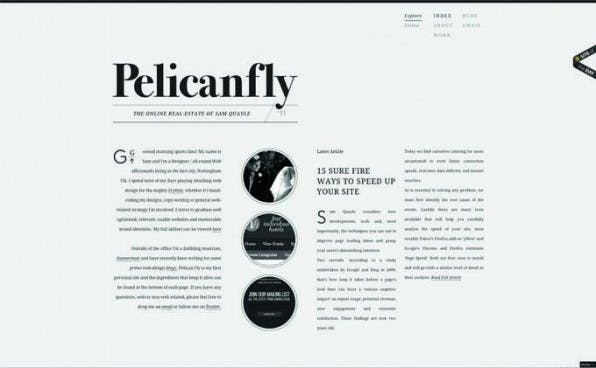
Wenn Websites auf verschiedene Bildschirmgrößen und Geräte reagieren sollen, brauchen sie dazu eine gewisse Flexibilität, die vor allem durch ein flexibles Raster in Kombination mit Media Queries erreicht wird. Wenn Spaltenbreiten, Bildgrößen und andere Dimensionen sich ändern, liegt es nahe, auch die typografische Erscheinung anzupassen. Bei veränderter Bildschirmgröße müssen dabei zwei Dinge abgewägt werden: Einerseits gilt es, den gewünschten „Charakter“ beizubehalten, andererseits ist der Umstand zu bedenken, dass Platz auf mobilen Geräten sehr wertvoll ist. Zwei Beispiele sollen dies veranschaulichen.
Die Website von Pelicanfly wirkt in der Desktop-Variante dank großer Logotypografie und viel Weißraum kontrastreich und interessant. Diesen Eindruck hat der Gestalter versucht, auf die mobile Variante zu übertragen, indem er die Logoschrift noch größer gesetzt hat und dadurch mehr als ein ganzes Darstellungsfenster füllt.
Er hat sich in diesem Fall ganz klar für die Bewahrung der spannungsvollen, aber auch gewagten Darstellung entschieden. Es ist durchaus grenzwertig, so viel Platz zu verschenken. In diesem Fall ist es aber legitim, denn bei der Website handelt es sich um sein persönliches Portfolio. Durch das Abweichen von der Norm macht er auf sich aufmerksam und vermittelt ein selbstbewusstes Auftreten. Die Schrift der Fließtexte hätte aber dennoch etwas größer ausfallen können.
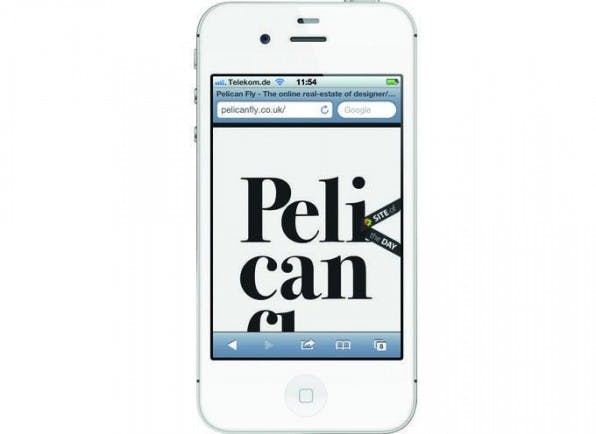
Die Online-Magazine Thinkvitamin und Smashing Magazine [4] verwenden in ihren Desktop-Ansichten Überschriften in einer passenden Größe. Sie stechen gut heraus, um als visueller Anker beim Überfliegen der Seite zu dienen, sind aber nicht zu auffällig, als dass sie den Leser ablenken.
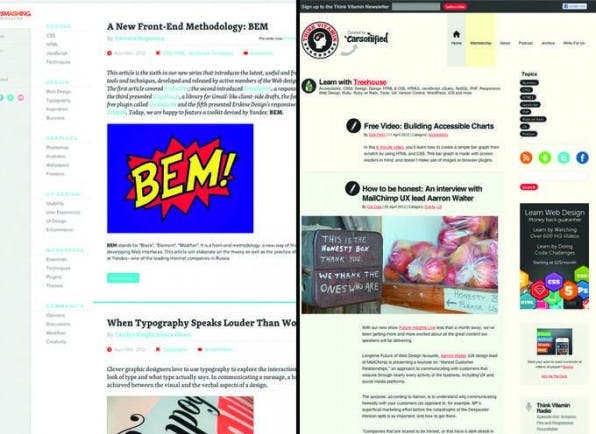
Bei den mobilen Varianten verändert sich diese ausgewogene Darstellung allerdings. Durch die geringe Breite mobiler Geräte brechen die Überschriften sehr oft um und nehmen somit auch vertikal sehr viel Platz ein. Das sorgt dafür, dass die Überschriften übermäßig stark auffallen und die Leser viel scrollen müssen, um die Inhalte zu durchforsten. Hier wäre es besser gewesen, mit einer angepassten Typografie zu reagieren und die Schriftgröße der Überschriften etwas zu verringern. Die Fließtexte hingegen haben eine gut lesbare Größe.